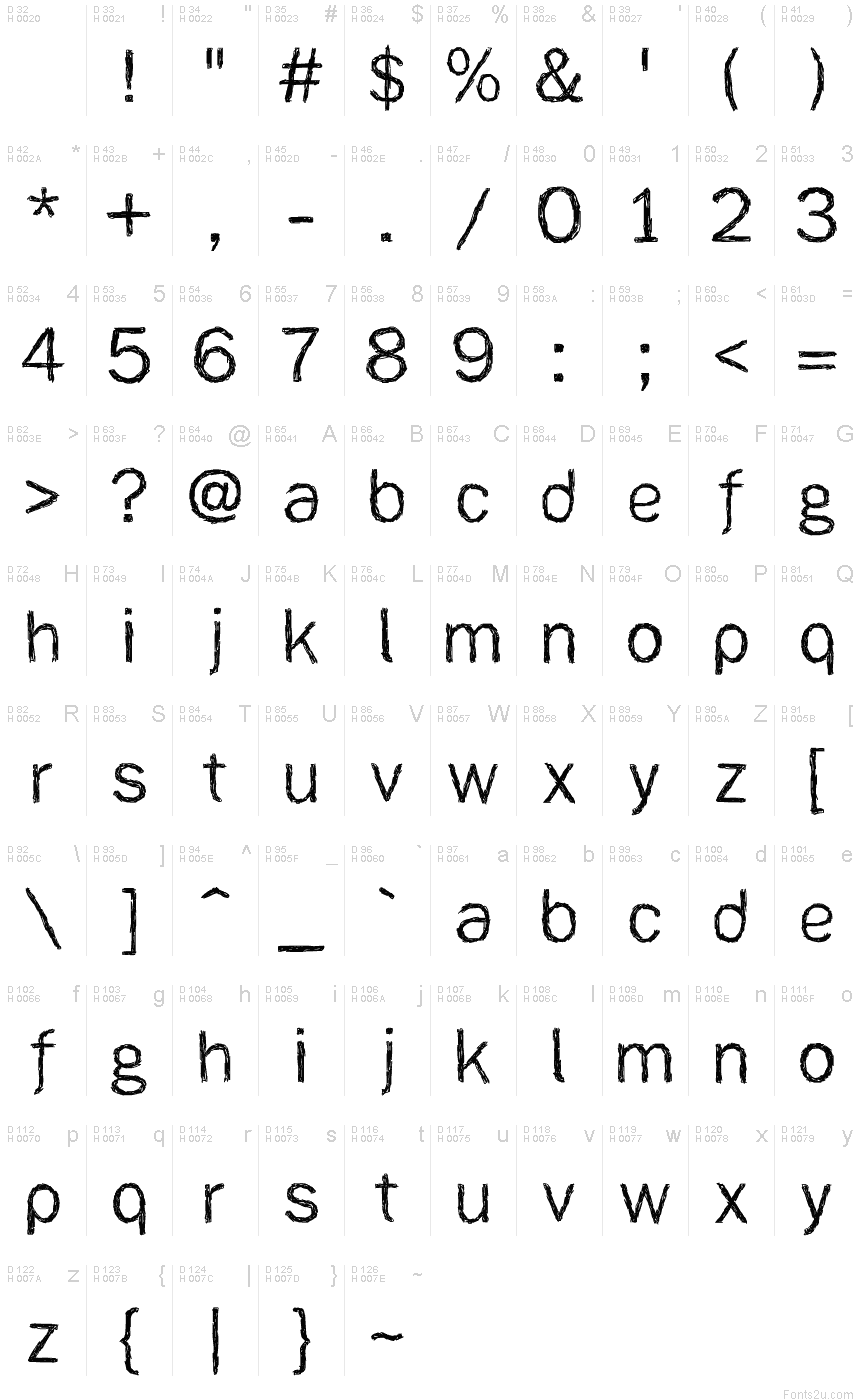
Ank to darmowy font w stylu trash o surowym, „wydrapanym” wyglądzie, który sprawia wrażenie bardziej nabazgranego niż narysowanego. Litery chwieją się, mają poszarpane krawędzie, nierówne pociągnięcia i drobne pęknięcia, dzięki czemu cały krój wydaje się podrapany, nerwowy i celowo niechlujny.
Pasuje do plakatów, zinów, okładek płyt, grafik skate’owych i tytułów, gdzie ta chaotyczna energia pomaga przekazać przekaz. Jako darmowy font, Ank najlepiej sprawdza się w krótkich słowach, nagłówkach i szybkich projektach brandingowych, ponieważ jego poszarpana, improwizowana faktura mówi sama za siebie.